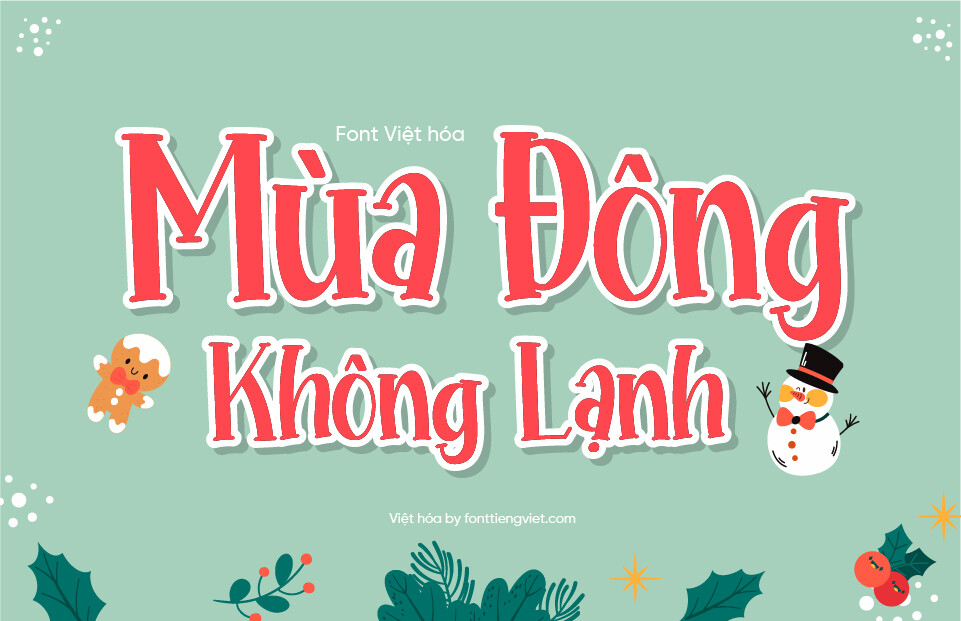
Giới thiệu về Font Việt hóa 1FTV Hopeful Christmas Solid – Giáng sinh
Trong không khí rộn ràng của những ngày cuối năm, việc tìm kiếm một bộ Font Chữ phù hợp để truyền tải thông điệp yêu thương là vô cùng quan trọng. Font Việt hóa 1FTV Hopeful Christmas Solid – Giáng sinh chính là lựa chọn hoàn hảo dành cho các bạn học sinh và giáo viên trong các hoạt động sáng tạo tại nhà trường. Với thiết kế dạng khối dày dặn và chắc chắn, bộ font này mang lại cảm giác ấm áp, vui tươi nhưng không kém phần trang trọng cho các sản phẩm truyền thông học đường.
Đặc điểm thiết kế nổi bật
Bộ font này được thiết kế theo phong cách hiện đại với các đường nét bo tròn mềm mại ở các góc, giúp giảm bớt sự thô cứng của các ký tự dạng Solid. Điều này giúp các em học sinh dễ dàng sử dụng trong việc thiết kế bảng tin, thiệp chúc mừng hoặc các bài thuyết trình chủ đề mùa đông. Sự đồng nhất trong cấu trúc chữ giúp nội dung luôn hiển thị rõ ràng và bắt mắt.
Ứng dụng thực tế của Font Việt hóa 1FTV Hopeful Christmas Solid – Giáng sinh
Sức hút của Font Việt hóa 1FTV Hopeful Christmas Solid – Giáng sinh nằm ở khả năng ứng dụng đa dạng trong nhiều hoàn cảnh khác nhau. Tại trường học, thầy cô có thể dùng font này để làm tiêu đề cho các thông báo nghỉ lễ hoặc trang trí sân khấu văn nghệ. Đối với các bạn học sinh, đây là công cụ tuyệt vời để làm đồ án thủ công hoặc thiết kế áo lớp chủ đề Noel.
Tính năng Việt hóa chuẩn xác
Điểm cộng lớn nhất của phiên bản này là đã được Việt hóa hoàn chỉnh với đầy đủ các dấu câu và ký tự đặc biệt trong tiếng Việt. Người dùng sẽ không gặp phải lỗi hiển thị dấu khi gõ nội dung, đảm bảo tính thẩm mỹ cao nhất cho mọi tác phẩm thiết kế từ đơn giản đến phức tạp.